筑紫書体、UDフォントなど高品位でバラエティ豊かなフォントを提供しています。多言語フォントも種類豊富に取り揃えています。
「LETS」のメリット
年間定額制で
新書体も使い放題
高品位でバラエティ豊かなフォントを取り揃えています。新たにリリースされるフォントも追加費用なしでご利用いただけます。
ほしいフォントも
すぐ見つかる
充実した検索機能で、直感的に文字を探せます。また、「気になるフォント」や「〇〇用フォント」など、目的に応じて自分だけのフォントリストを作れます。
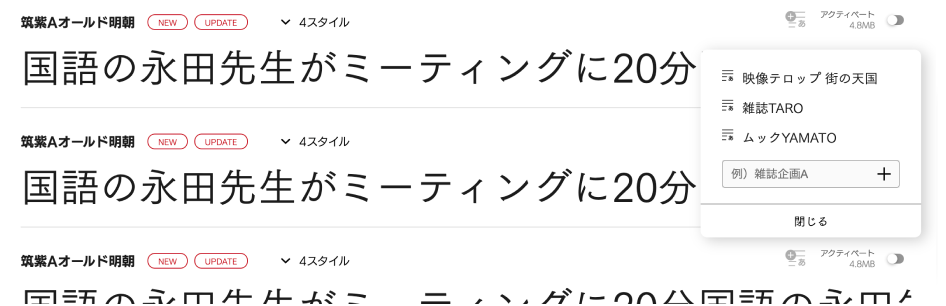
ON/OFFの動作ひとつで
フォントを整理
使いたいフォントはON、使わないフォントはOFF。ボタンをひとつ押すだけで、制作ツール上のフォントメニューに使いたいフォントだけを表示できます。
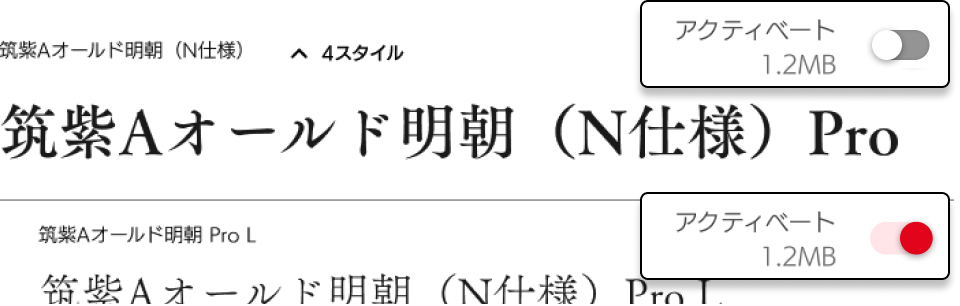
グループ・個人同士で
共有できるフォントリスト
使用したいフォント、お気に入りのフォントなどをリストで管理できます。作成したリストはURLを発行することで共有できます。
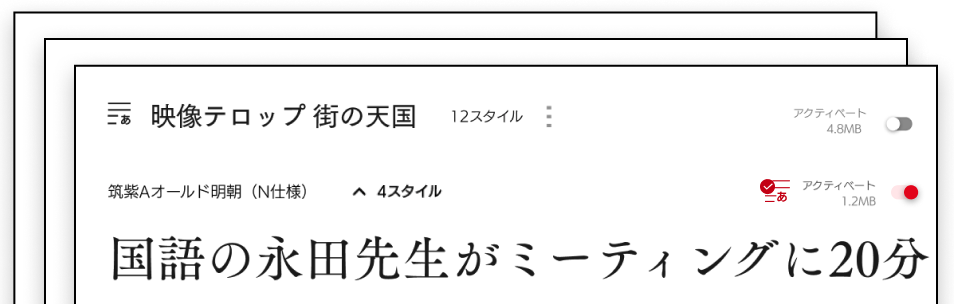
複数のアカウントを
グループで一括管理
「グループ」を作成した場合は複数のライセンス・アカウントの管理ができます。「オーナー」、「契約管理者」、「アカウント管理者」、「メンバー」と役割を分担し会社・部署・プロジェクトごとなどに管理・運営・利用ができます。
フォントを組み込み、
利用できるオプション
アプリでも、バラエティ豊かで高品位なフォントを
サーバー上で動作するアプリケーション内でもLETSフォントがご利用いただけます。サーバーサイドでドキュメントやデザイン出力にフォントの組込が可能となります。
フォントワークス LETS
Monotype LETS
Helvetica、Frutiger、Optima をはじめ、Monotype 株式会社が提供している世界的に有名な欧文フォントや多言語フォントを使用できます。
書籍や広告からデジタルコンテンツまで、幅広い人気を誇る毛筆書体を取り扱う株式会社昭和書体の各種フォントを使用できます。
イワタ LETS
活字時代からの書体開発の歴史と書籍からユニバーサルデザイン(UD)まで多くの使用実績を誇る株式会社イワタの各種フォント『イワタコレクション』を使用できます。
モトヤ LETS
「可読性の良さ」と「文字の美しさ」を特徴とした、60年以上の歴史を持つ株式会社モトヤの各種フォント『モトヤコレクション』を使用できます。
YOON LETS
韓国市場にて最も使用され、書体と関連したデザインソリューションも展開しているフォントメーカーのYoonDesign Group Inc.の各種フォントを使用できます。
方正 LETS
中国市場でトップシェアを誇るフォントメーカーHOUSEI株式会社のフォントを使用できます。